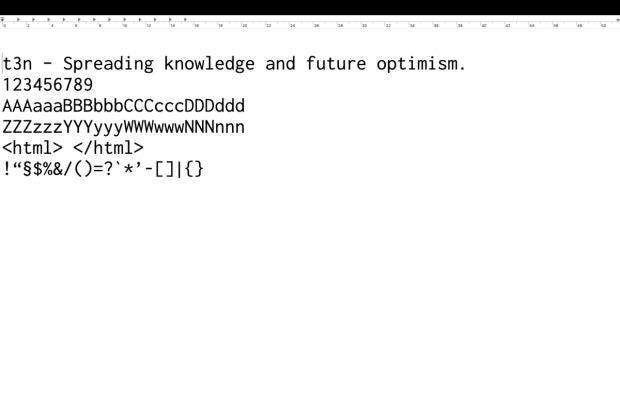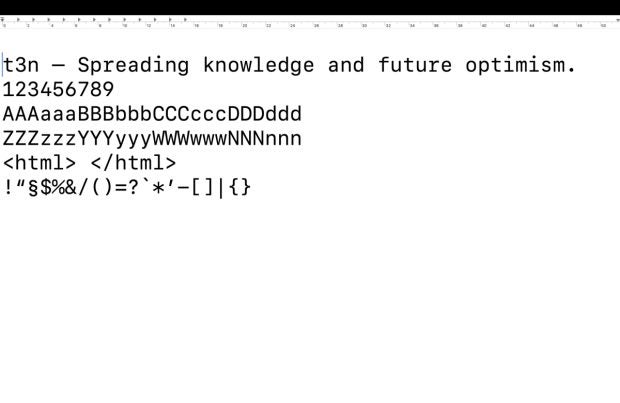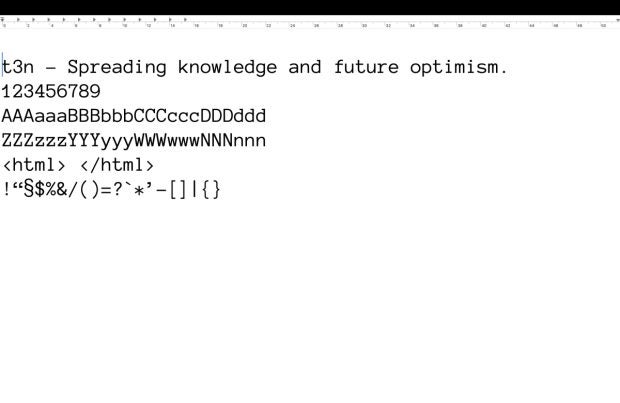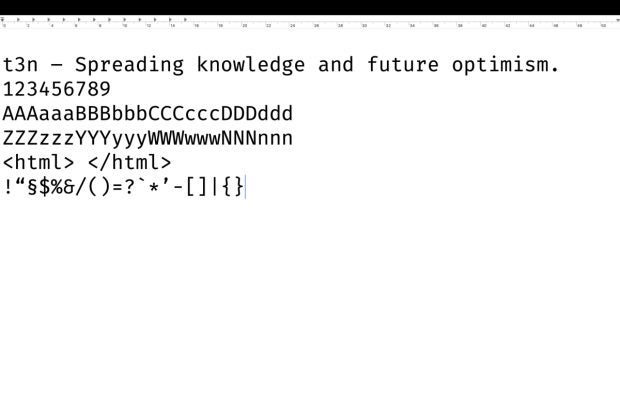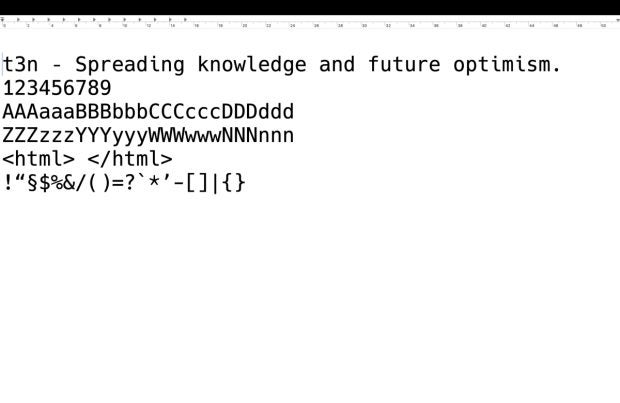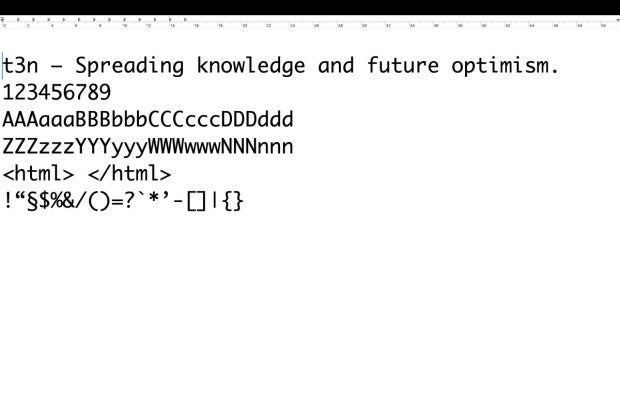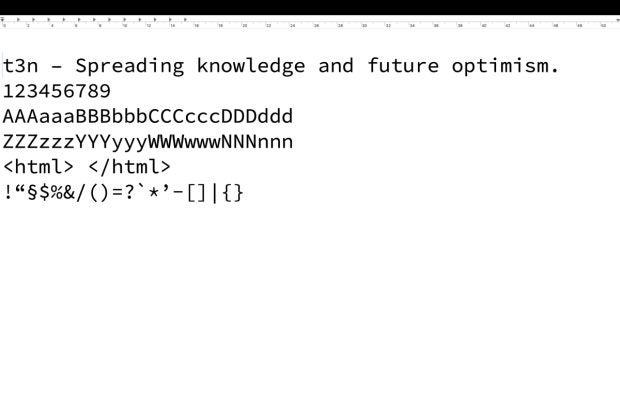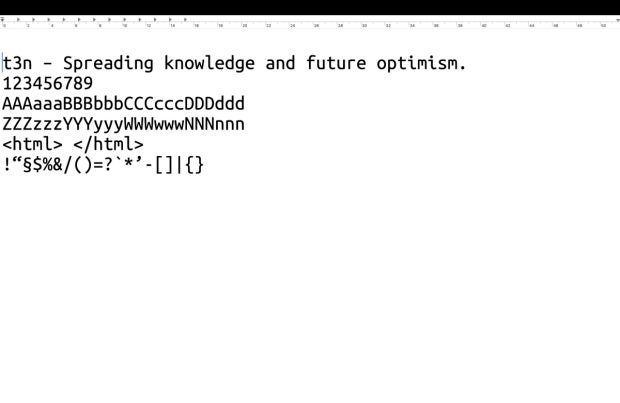
Coding-Fonts: Diese 8 Gratis-Schriften schonen deine Augen
Entwickler:innen und Designer:innen brauchen Schriften, die die Augen schonen und das Erkennen unterschiedlicher Buchstaben und Symbole erleichtern. Wir haben beliebte Coding-Fonts für euch zusammengetragen, die ihr gratis herunterladen könnt.
Entwickler:innen und Designer:innen verbringen oftmals Stunden damit, am Rechner zu sitzen und auf ihren Code zu starren. Um dabei die Konzentration aufrechtzuerhalten, effizient zu arbeiten und Fehler zu vermeiden, sollten sie die dabei verwendete Schriftart sorgfältig auswählen. Gute und angenehme Lesbarkeit gehört zu den Hauptkriterien für hilfreiche Coding-Fonts. Dabei haben sich vor allem Monospace-Fonts, also Schriften mit fester Zeichenbreite, die auf die feste Typenbreite von Schreibmaschinen zurückgehen, bewährt. Sie leiten das Auge durch ihre an einem imaginären Raster orientierte Ordnung auch durch lange Code-Reihen und erlauben die Unterscheidung einzelner Charaktere.
Ein weiteres gängiges Merkmal, das viele Schriften für Programmierer:innen teilen, ist der weitgehende Verzicht auf Serifen und sonstige Schnörkel, denn auch diese wirken auf Dauer ermüdend auf die Augen. In den vergangenen Jahren sind immer mehr Schriften erschienen, die sich speziell an die Bedürfnisse von Coder-Entwickler:innen richten. Die wichtigsten von ihnen findet ihr in der nachfolgenden Übersicht.
1. Source Code Pro
Ein Texteditor zeigt die Schriftart Source Code Pro an.
Source Code Pro ist ein Dauerbrenner unter Coding-Fonts. (Bild: t3n)
Der Programmier-Font Source Code Pro ist 2012 von Paul D. Hunt für Adobe entwickelt worden und gehört mittlerweile zu den meistgenutzten und beliebtesten Entwickler:innen-Fonts überhaupt. Er baut auf der Adobe-Schrift Source Sans auf, sorgt aber durch adaptierte Buchstabenhöhen, weitgehenden Verzicht auf Serifen und die Vergrößerung wichtiger Symbole wie „<“, „>“, Klammern oder Satzzeichen für bessere Lesbarkeit. Die Schrift steht unter Open-Source-Lizenz und ihr findet sie bei GitHub zum Download.
2. Hack
Ein Texteditor zeigt den Font Hack an.
Der 2015 veröffentlichte Coding-Font Hack von Sourcefoundry erfreut sich zunehmender Beliebtheit. (Bild: t3n)
Der Open-Source-Font Hack basiert auf der ebenfalls beliebten Entwickler:innen-Schrift DejaVu sans mono und wird von seinen Macher:innen als wahres „Arbeitspferd für Code“ beschrieben. Er zeichnet sich durch gute Lesbarkeit gerade bei kleinen Schriftgrößen und strategisch platzierte Serifen aus und hebt außerdem die für das Programmieren wichtigen nicht alphabetischen Zeichen hervor. Im Hack-Playground von Sourcefoundry.org könnt ihr Hack in Aktion sehen und auch einige weitere Coding-Fonts ausprobieren.
3. Inconsolata und Inconsolata‑g
Ein Texteditor zeigt den Font Inconsolata an.
Die Schriftart Inconsalata ist für Entwickler:innen gratis. (Bild: t3n)
Mit Inconsolata folgt eine Open-Source-Schrift, die auf den grafischen Elementen von Consolas, aber auch auf den älteren Schriften Avenir und Letter Gothic aufbaut. Designer Raph Levien hat besonders darauf geachtet, dass Inconsolata nicht nur bei kleinen Schriftgrößen gut aussieht, sondern sich auch problemlos skalieren lässt, ohne an Reiz einzubüßen. Inconsolata findet ihr auch bei Google Fonts.
Bei Inconsolata‑g wiederum handelt es sich um eine modifizierte Version von Inconsolata, bei der einzelne Schriftzeichen zwecks noch besserer Lesbarkeit angepasst worden sind. So sind etwa die Anführungszeichen gerade und nicht schräg, Ziffern sind leicht vergrößert und der Slash durch die Null wird durch einen innen liegenden Punkt ersetzt. Auch Inconsolata‑g steht unter Open-Source-Lizenz.
4. Fira Mono
Ein Texteditor zeigt Text in der Schriftart Fira Mono an.
Fira Mono gehört nach wie vor zu den beliebtesten Schriftarten für Entwickler:innen. (Bild: t3n)
Fira Mono ist die Monospace-Variante der Schrift Fira Sans, die Erik Spiekermann und weitere Designer:innen 2013 für Mozillas Open-Source-Betriebssystem Firefox OS entwickelt haben. Sie basiert auf Mozillas Hausschrift FF Meta und weist außerdem einige Ähnlichkeiten mit Adobes Source Code Pro auf, wird aber zuweilen für noch bessere Lesbarkeit gepriesen. Fira Mono steht, wie die gesamte Fira-Schriftfamilie, unter Open-Source-Lizenz. Ihr findet die Schrift auf GitHub oder auch bei Fontsquirrel.
5. SF Mono
Ein Texteditor zeigt die Schriftart SF Mono an.
SF Mono basiert auf San Francisco, einer von Apple entwickelten Schriftart. (Bild: t3n)
SF Mono ist aktuell die Standardschriftart auf Macs für das Terminal und die Entwicklungs­umgebung Xcode. Dabei handelt es sich um die Monospace-Variante der Systemschrift San Francisco, die das Unternehmen selbst designt hat. Sie wird von Entwickler:innen auf Websites wie Slant als gut lesbar beschrieben. Allerdings ist sie ab Werk nicht systemweit verfügbar. Das könnt ihr ändern, indem ihr den Ordner Dienstprogramme über den Finder öffnet. Klickt dann rechts auf Terminal und auf Paketinhalt anzeigen. Navigiert dann durch die Ordner Contents und Resources zu Fonts. Wählt alle Dateien aus und klickt nach einem Doppelklick auf Installieren. Danach steht SF Mono auch in anderen Programmen zur Verfügung.